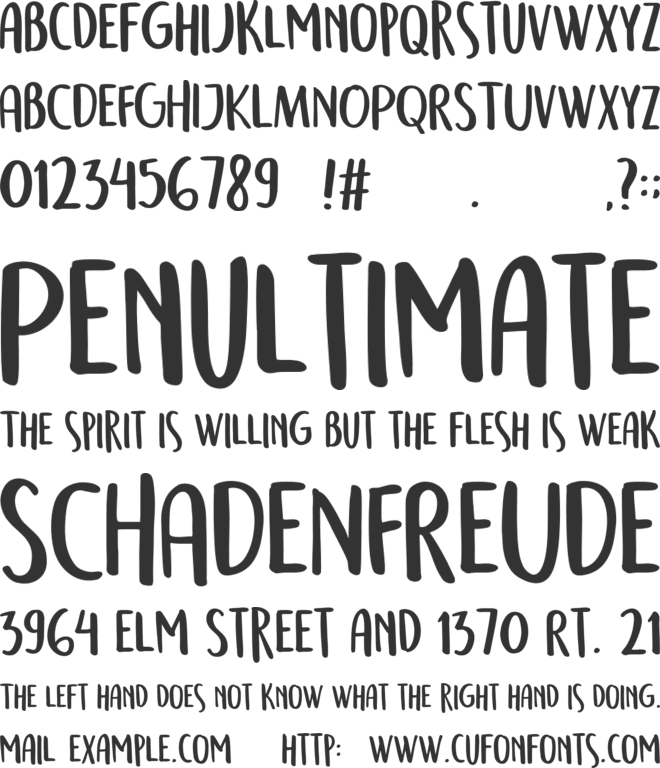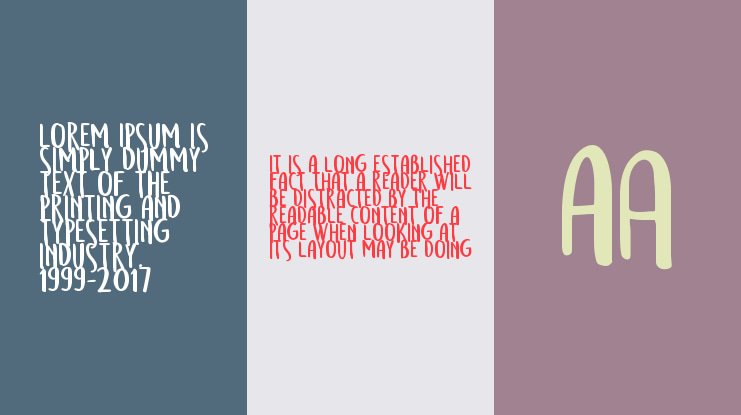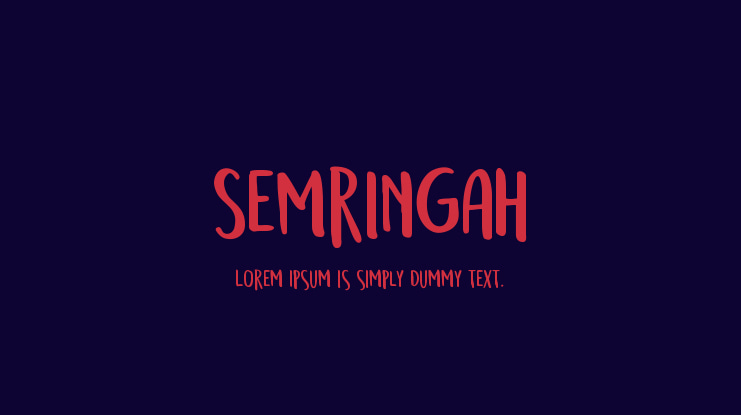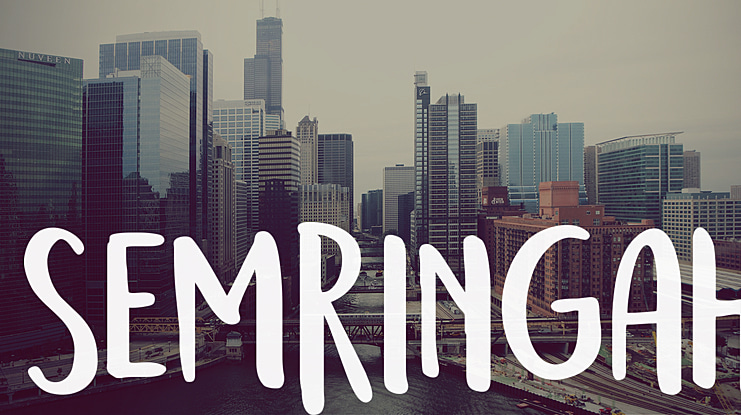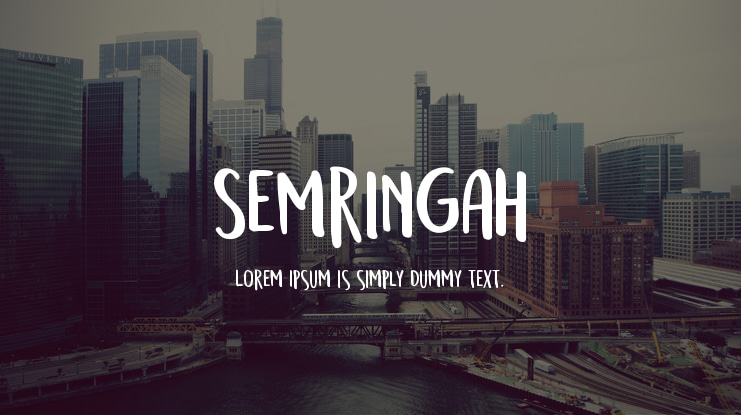
Semringah Font
Semringah: fontasi cuma-cuma cuma untukmu! Semringah, sesuai namanya, mampu membuat hari-harimu penuh keceriaan! Tuliskan kata-kata dalam fontasi Semringah untuk mendapatkan kesan yang ceria, bahagia, ramah dan mudah.